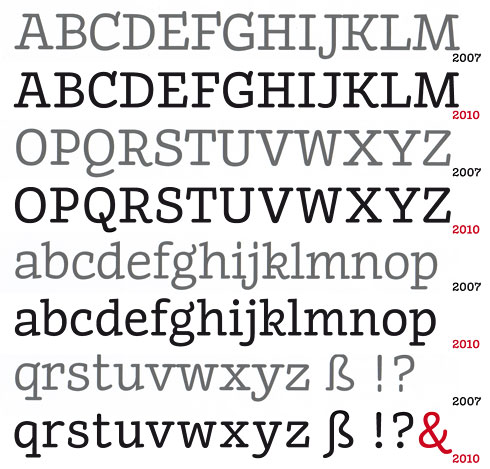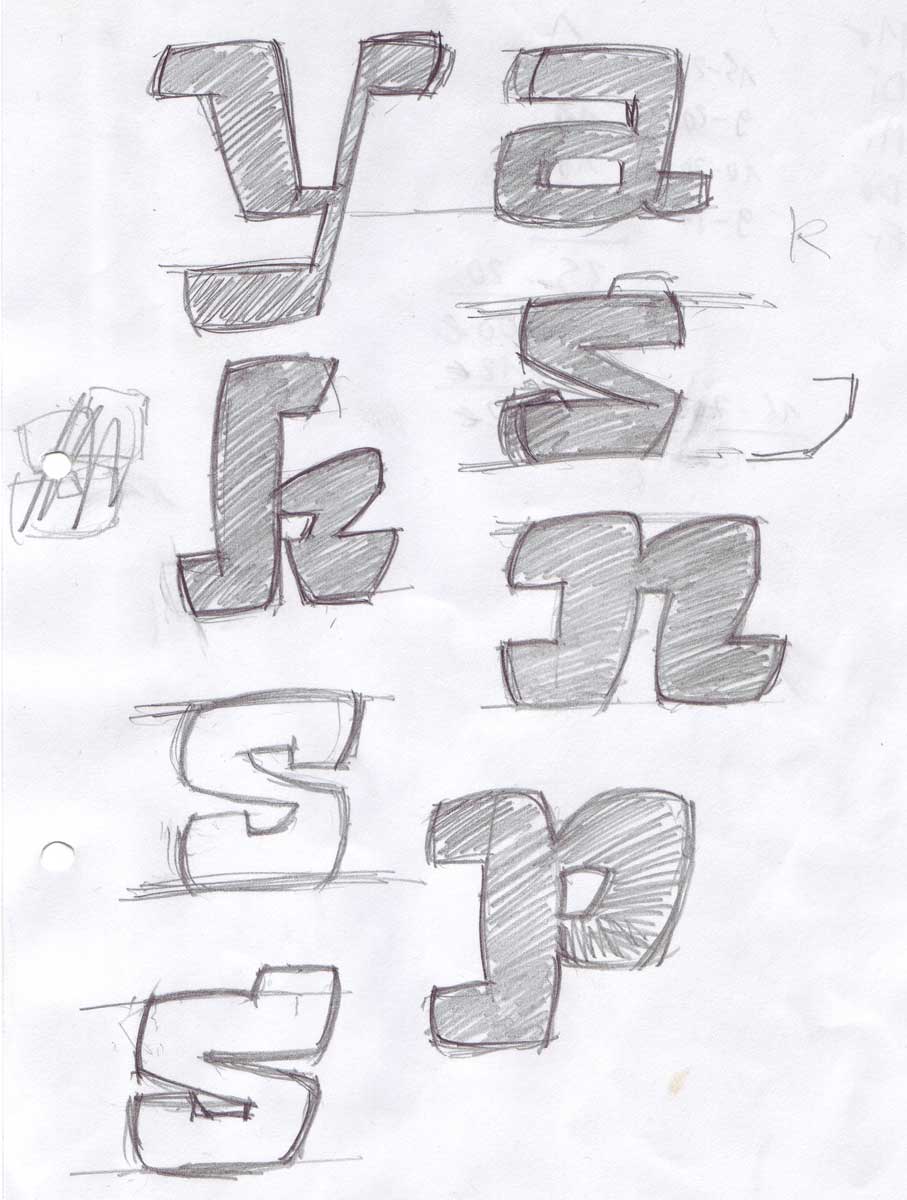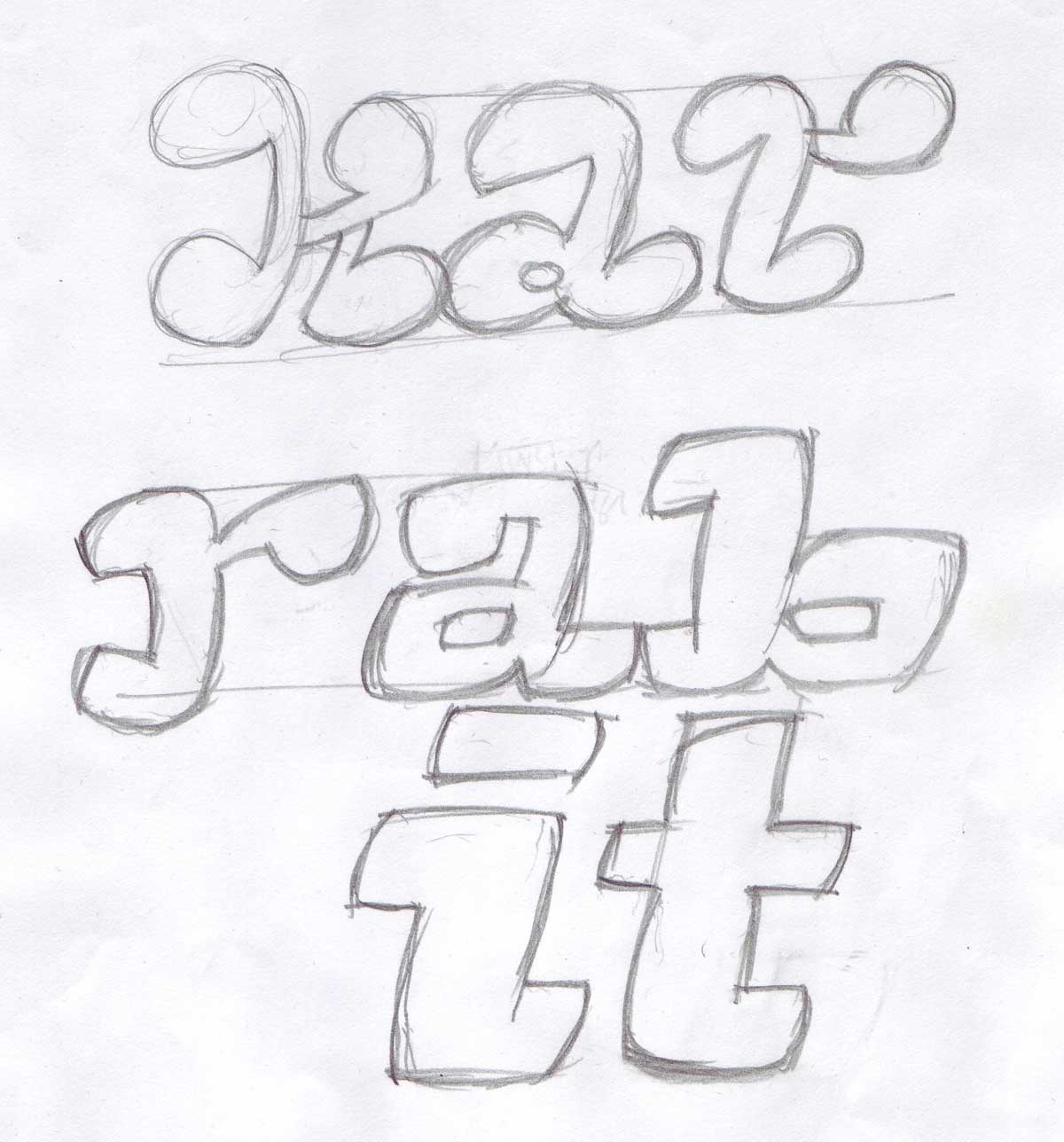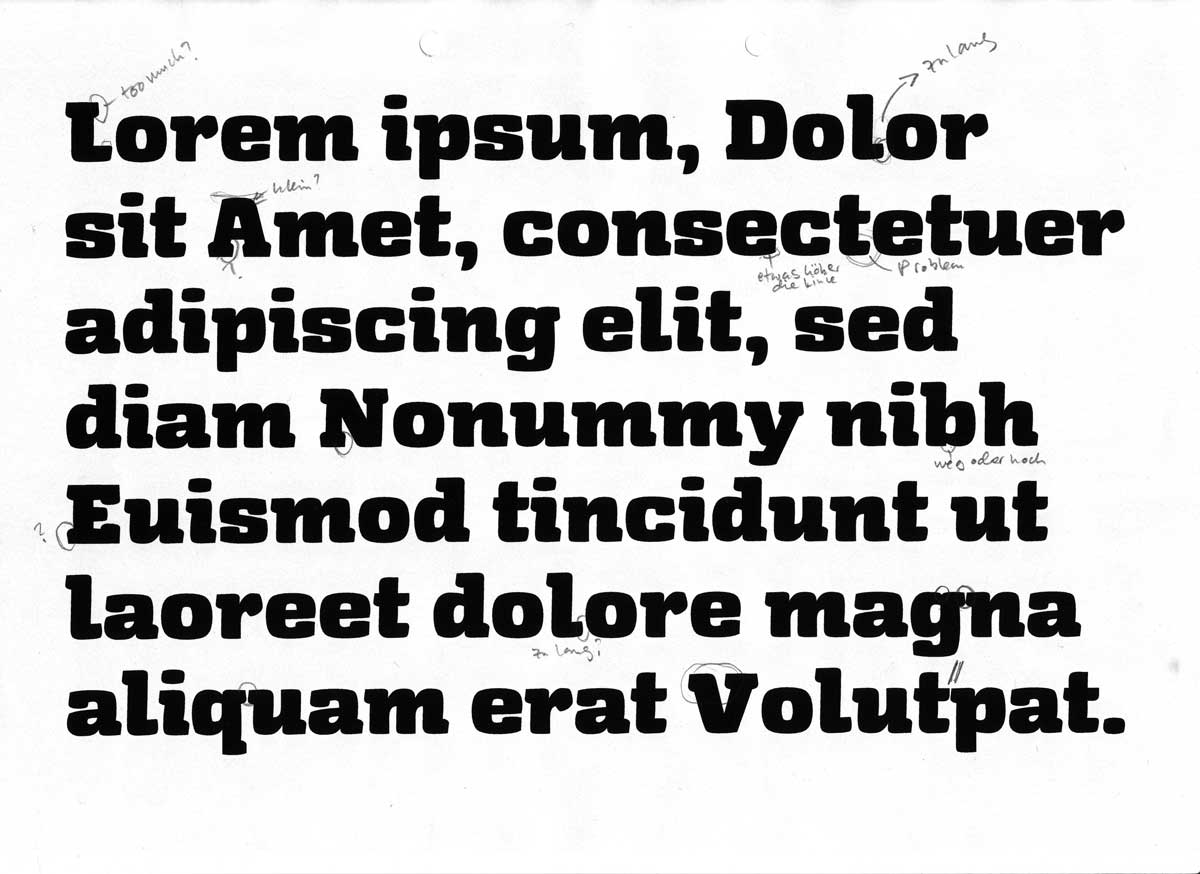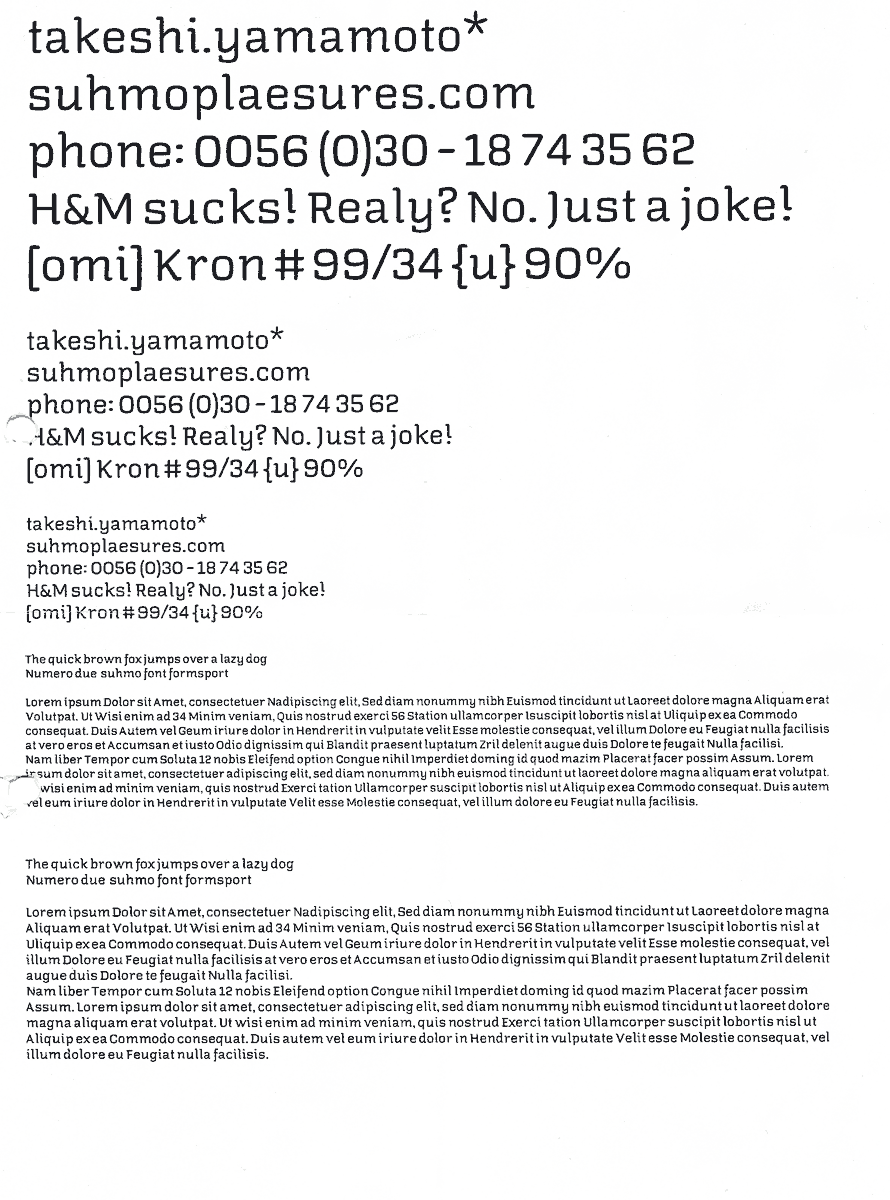
Wer sich an meine PDF-bestückten Beiträge Die 12 häufigsten Satzsünden und die Berliner-Schriftausstellung-Treppe erinnert, wird bemerkt haben, dass ich im Moment mit einer Lieblingsschrift gestalte. Es ist die neue FF Suhmo, entworfen von Alex Rütten. Weil Suhmo alle Charakteristika einer Korrespondenzschrift aufweist, hatte ich sie auch Oliver Reichenstein für (die gestern erschienene) App iA Writer vorgeschlagen, wobei ich heute sagen muss: Nitti Light von Bold Monday ist exakt der richtige Zeichensatz für den spartanischen Writer, FF Suhmo wäre zu verspielt gewesen.
Ich wollte mehr wissen, über FF Suhmo und habe mir letzte Woche ein paar Informationen bei ihrem Schöpfer eingeholt. Die erste Skizze für die Schrift entstand bereits 2004 – im Aufenthaltsraum einer Jugendherberge in Frankfurt am Main. Zu diesem Zeitpunkt ging die Form der Buchstaben noch stark in Richtung Graffiti: Die Zeichen wirkten in der kräftigsten Strichstärke wie aufgepustet. Die Formen waren gleichzeitig noch sehr konstruiert. »Die Proportionen erinnern bisweilen an Eurostyle, obwohl das unbeabsichtigt war. Mit dem ersten Ansatz bin ich leider lange Zeit nicht weitergekommen. Und so habe ich die Papiere erst mal zur Seite gelegt.« erinnert sich Alex Rütten heute.
Zwei Jahre später setzte er für einen Plakatentwurf die »American Typewriter« ein und war überrascht von ihren Qualitäten als Headline-Schrift. Als kurz darauf Sony-Ericsson die gleiche Schrift für seine Handy-Reklame entdeckte, kam er erstmals auf die Idee, seine Suhmo in diese Richtung weiter zu entwickeln. Und so kramte Alex Rütten die Skizzen aus der Jugendherberge wieder aus, um sie nach und nach mit dem Typewriter-Design zu mixen. »Ich fand dass Ergebnis brauchbar. Die Zeichen wurden organischer, die x-Höhe größer und die Slab-Serifen brachten Klarheit und Ruhe im Textfluss.« so sein Urteil in der Rückschau.
»Zu jener Zeit begann ich mich sehr für alte Neon-Reklame Schrift in Berlin zu Interessieren.« fährt Rütten fort. Besonders an italienischen Restaurants aus den 60er und 70er Jahren fand er bemerkenswerte Schriftzüge, die häufig durch ihre skurrilen Schlaufen auffielen. Dieses Element nahm er schließlich mit in das Konzept von Suhmo auf. Vor allem in den Italic-Schnitten finden sich heute einige solcher Details wieder.
Abschließend hatte ich noch einige Fragen an Alex Rütten, die er mir in einem kurzen Gespräch beantwortete:
Fontblog: Wie würdest du einem Laien den Charakter von FF Suhmo beschreiben?.
Rütten: Ihr Charakter ist aus meiner Sicht verspielt, aber gleichzeitig funktional. Alle Details sind so dosiert, dass sie in kleineren Textgrößen nicht zu sehr aus dem Textbild rausstechen oder den Lesefluss stören. Ansonsten ist Suhmo freundlich, etwas launisch, in den Italics hat sie etwas Botanisches.
Wie hat sich das Aussehen der Schrift während des Designprozesses verändert?
Im Designprozess hat sich vor allem durch das unermüdliche Feedback von Christoph Koeberlin bei FSI einiges getan. Viele Details, die zu unpraktikabel oder zu eigensinnig waren, sind weggefallen. Zum Beispiel hatte das Q eine extravagante Schlaufe, oder das J unten noch eine Serife, die der Grundlinie gefährlich nah kam. Eine andere Änderung war das Herausarbeiten des Wechselstrichs, da am Anfang die Horizontale noch zu stark war, so dass sie optisch zu dick wirkten. Auch die Verjüngung in den Übergängen war zu gering. Die Lesbarkeit und die Proportionen der Zeichen zueinander wurden mit der Zeit immer besser. Einige Großbuchstaben waren noch zu schmal, andere Zeichen liefen zu breit.
Hattest Du schon früh das Modell einer Korrespondenzschrift im Kopf?
Den Ausdruck Korrespondenzschrift höre ich jetzt von Dir zum ersten Mal, von daher kann ich die Frage verneinen. Wenn ich das jetzt richtig nachgeschaut habe, versteht man unter einer Korrespondenzschrift eine Schrift für den Briefverkehr, also eine Ergänzung zur Hausschrift, oder? Wird da nicht meistens Arial genommen?
OK, wieder etwas gelernt: So tickt die neue Generation von Schriftentwerfer. Welcher Buchstabe ist dein Liebling?
Vor allem mag ich das e, mit dem Unterbiss. Und mit der Form des a bin ich ebenfalls sehr zufrieden. Mein Liebling ist vielleicht das g mit diesem hochgeklappten Ohr, das wie eine Baseballcap aussieht. Für mich haben diese Zeichen einen eigenen Charakter. Wenn ich mir die Schrift jetzt anschaue, fallen mir besonders die Ligaturen noch angenehm auf.
Unermüdliches Feedback ist eins – es anzunehmen und unermüdlich-geduldig daran weiterzuarbeiten das Entscheidende …
Kompliment, Alex, hat großen Spaß mit Dir gemacht und ich freue mich, daß sie jetzt endlich veröffentlicht ist!
Hm. Die Museo mit etwas Courier versetzt…
Nach der ausführlichen schilderung des entstehungsprozesses ist das ja wohl ein ziemlich dusseliger kommentar…
Da ist nichts „versetzt“. Die bilder, die Alex im kopf hat, lassen sich nicht auf bestimmte vorlagen reduzieren. Und selbst wenn ein schriftentwerfer eine andere schrift im kopf hat, wird er sie aus der erinnerung immer so zeichnen, wie er sie sich angeeignet hat, nicht wie sie „in echt“ ist. Mach mal die probe und lass einige kollegen die gleiche schrift aus dem kopf zeichnen und du wirst dich wundern, wie unterschiedlich die ergebnisse aussehen.
Auf jeden fall ist die FF Suhmo eine ganz eigene form, egal was irgendwelche neidköppe sagen.
mir ist die schrift schon vor wochen bei fontshop.com aufgefallen, eben weil sie eine art ‘frische american typewriter’ ist, allerdings hatte ich die black-schnitte noch nicht entdeckt. wahnsinn! damals war sie allerdings bei .de noch nicht gelistet, schön das sie jetzt auch hier zu haben ist. vorgemerkt…
Das Minuskel “k” 2010 geht ab! Und das 2010 “j” find ich jetzt wesentlich besser als das von 2007. Gefällt mir der Font!